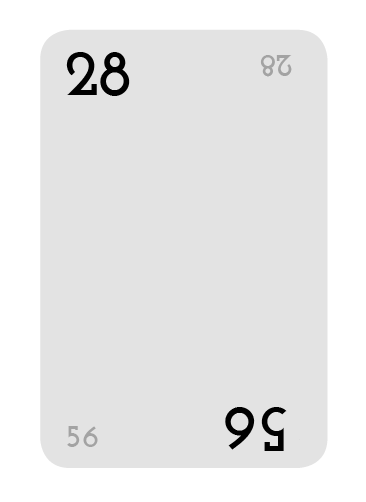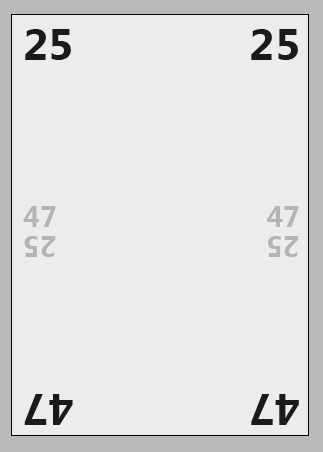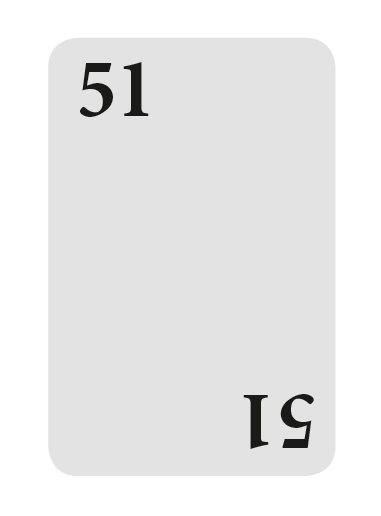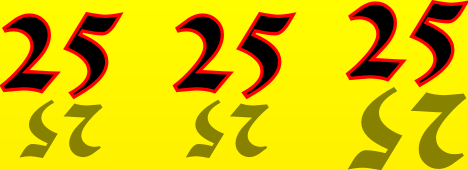
Problem beim Zentrieren von unteinander stehenden Texten mit proportionaler Schrift
Ich habe eine Frage zur Ausrichtung bzw. Zentrierung von untereinander stehenden proportionalen Schriften.
Ich möchte eine Zahl (bspw. 25) einmal groß, und direkt darunter gespiegelt in kleinerer Schriftgröße zentrieren. Da es sich dabei um eine proportionale Font handelt und daher die Zahlen unterschiedlich breit sind, kann ich diese zwar zentrieren, aber das Ergebnis sieht optisch nicht so schön aus.
Gibt es dazu eine Regel, wie man so etwas optisch ansprechend gestaltet oder ist hier einfach Handarbeit gefragt?
Ich hoffe, ihr könnt mir dabei helfen.
Soll das am Ende aussehen wie eine natürliche Spiegelung? Dann wird es mit einer kleineren Schriftgröße sicher nicht ansprechend aussehen. Warum soll die Spiegelung denn kleiner sein?
Ich kapier die Frage nicht … meinst du das so?
Ja, genau so meinte ich es. Konkret geht es da um die Gestaltung von Spielkarten. Die kleinere Zahl ist dazu gedacht, dass der Spieler der gegenüber sitzt den Wert leichter erkennen kann. Diese Zahl sollte jedoch nicht allzu prominent erscheinen.
Eine Regel gibt es da nicht für die Gestaltung.
Eine Möglichkeit wäre aber, dass Du die verkleinerte, gespiegelte Zahl in einem etwas dickeren Schriftschnitt setzt als die große »Hauptzahl«, damit Du eine ausgewogene Gewichtung der beiden Zahlen erhältst.
Wenn Dich der optische Versatz stört, der durch die unterschiedlichen Schriftgrößen entsteht, dann könntest Du als gestalterischen Kniff eine feine Trennlinie mittig zwischen die beiden Zahlen setzen. Das bringt optische Ruhe in die Angelegenheit und die Linie beschreibt gleichzeitig die Achse, an der gespiegelt wurde.
Ja, genau so meinte ich es. Konkret geht es da um die Gestaltung von Spielkarten. Die kleinere Zahl ist dazu gedacht, dass der Spieler der gegenüber sitzt den Wert leichter erkennen kann. Diese Zahl sollte jedoch nicht allzu prominent erscheinen.
Warum nicht so?
Beide Kartenenden weisen unterschiedliche Werte auf, daher kann ich das nicht so umsetzen wie in traditionellen Kartenspielen.
Mir ging es darum zu wissen, ob es so etwas wie einen Trick zum Finden einer "optischen" Mitte gibt.
Habe mal ein Beispiel eingefügt.
Leider kann ich den Vorschlag auch nicht so umsetzen, da man ja Karten normalerweise gefächert auf die Hand nimmt, und man dann entweder auf den Wert links oder recht oben schaut.
Aber den Trick von Kathrinvdm mit der feinen Hilfslinie werde ich mal ausprobieren.
… man dann entweder auf den Wert links oder recht oben schaut. …
Könntest du mal ein Beispiel zeigen? Ich versteh immer noch nicht, welcher Wert denn wo stehen soll …
Die Werte stehen in jeder der vier Karten-Ecken. So wie zum Beispiel bei diesem Kartenspiel:
Nur dass bei allen vier Zahlen die Spiegelung in kleinerer Größe hinzukommt.
Du beschreibst 2 Szenarien:
a) Der Spieler hält die Karten aufgefächert auf der Hand -> in dem Fall sieht der gegenüber Sitzende gar keine Zahl.
b) Die Karte liegt vor dem Spieler auf dem Tisch -> in dem Fall sehen beide Spieler beide Ecken.
???
Ja, stimmt. Das sind zwei Szenarien. So wie bei einem normalen Stichspiel.
Einerseits hat ein Spieler seine verdeckte Kartenhand, die nur er sieht. Diese Kartenhand hält ein Spieler normalerweise gefächert auf seiner Hand. Je nach Vorliebe werden die Karten dann so gehalten, dass die Werte entweder links oder rechts sichtbar sind. Das ist der Grund warum heutzutage die Werte in beiden Ecken stehen.
Beim Ausspielen einer Karte, d.h. wenn er diese offen vor sich ablegt, sollen die Werte gut erkennbar für beide Spieler sein. Der gegenübersitzende Spieler kann den Wert dann einfach anhand der kleineren Zahl erkennen.
Aber im Grunde geht es nicht darum, wo die Werte stehen sondern wie die große und die kleine gespiegelte Zahl optisch schön zentriert werden können.
… wie die große und die kleine gespiegelte Zahl optisch schön zentriert werden können. …
Ich bin immer noch bei der Frage, ob sie das müssen – oder ob sich nicht eine hübschere Anordnung fände ;-)
ja, da gebe ich dir Recht. Darüber habe ich mir auch lange Gedanken gemacht. Vor allem, da hier natürlich die Gefahr besteht, dass die Karten zu überfrachtet wirken. Es sind ja quasi acht Zahlen auf der Karte, in jeder der vier Ecken zwei.
Ich hatte erst versucht, das Ganze ohne die gespiegelte Zahl zu gestalten. Allerdings habe ich dabei gemerkt, dass es unheimlich anstrengend ist, die Zahlen im Kopf umzudrehen.
Wenn einfach in jeder Ecke eine Zahl steht, dann sieht doch auch der Gegenüber zwei Zahlen richtig rum. Nämlich die, die beim in der Hand halten unten und auf dem Kopf stehen. Da brauchst du doch keine Spiegelung.
das ist ein interessanter Vorschlag, zumal dabei insgesamt weniger Zahlen auf der Karte sind.
Ich werde mal prüfen, inwiefern ich das ansprechend umsetzen kann.
Oder so?
auch das ist eine interessante Möglichkeit.